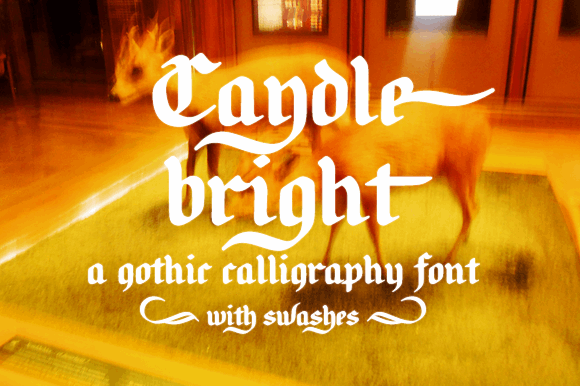
Esta é uma amostra do “Candlebright”, uma fonte de calligrafia gótica com 345 caracteres, incluindo letras A-Z e a-z, números de zero até nove, acentos, pontuação e símbolos. Este conjunto único de características, que inclui alterações estilísticas, sobrescricas, ligaduras e um extra de ornamentos matchantes, adiciona uma captação visual única à sua obra final. A “Candlebright” é perfeita para aqueles criadores de design em busca de algo surpreendente e elegante. Suas linhas finas e detalhes refinados fazem dela uma escolha sólida tanto para aplicações comerciais quanto para projetos pessoais, oferecendo liberdade criativa sem abrir mão da funcionalidade desejada. Agora é o momento de experimentar essa fonte gótica que toca com delicadeza e autoridade. A “Candlebright” é uma escolha inteligente para quem busca um toque único em seus projetos de design, seja você designer gráfico, ilustrador ou tipógrafo.
Designer: Justlikethistrain